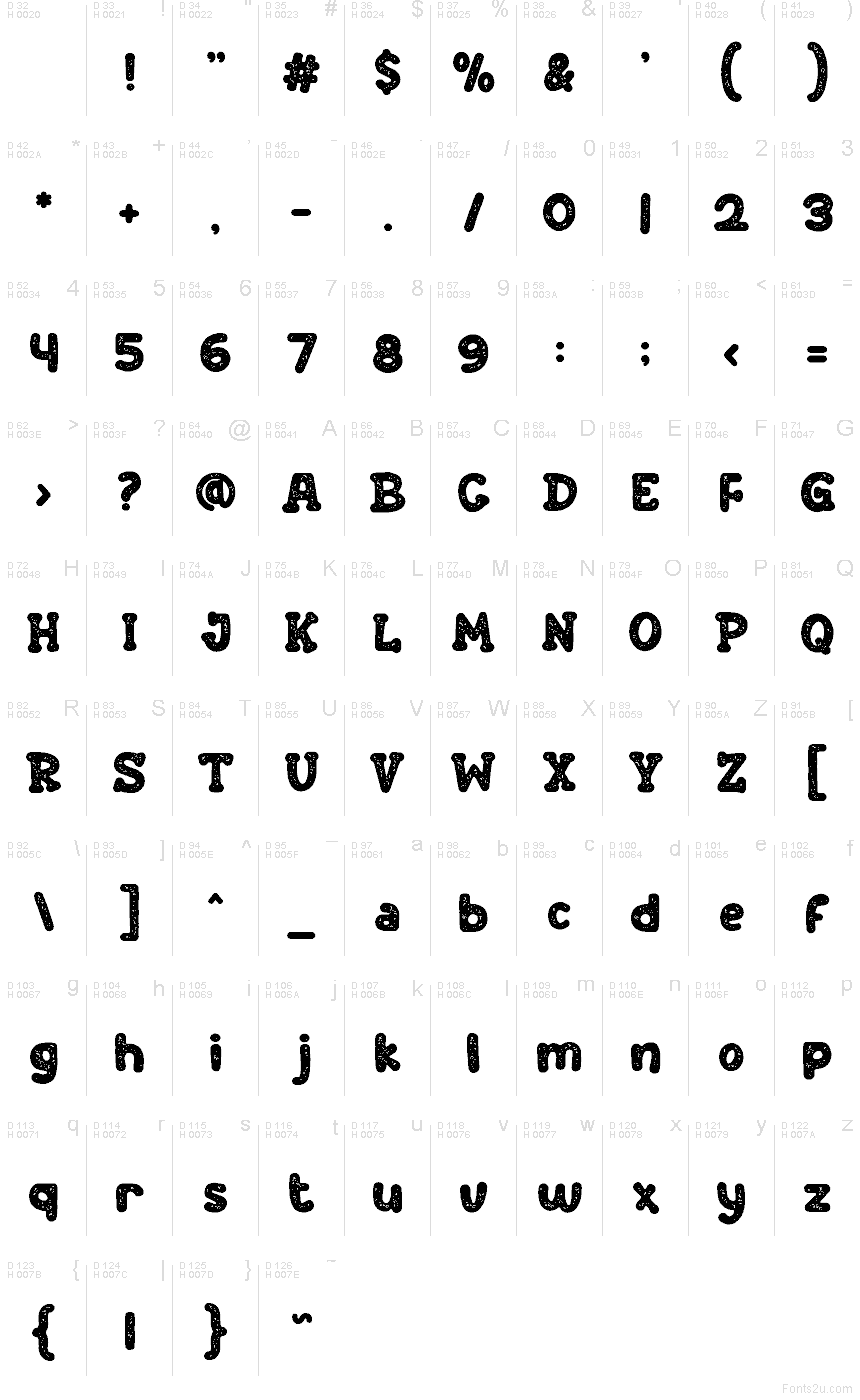
Crayon Craft Four od Putracetol Studio to bezpłatny, erodowany krój pisma typu display, stylizowany na rysunkowy. Charakteryzuje się miękkimi, zaokrąglonymi literami oraz woskową teksturą pełną przetartych drobinek. Ten efekt przypominający kredę i świecówkę przenika cały projekt, nadając czcionce rzemieślniczy, szkolny klimat, zamiast typowego, generycznego efektu postarzenia.
Świetnie sprawdzi się na okładkach książek dla dzieci, plakatach szkolnych, opakowaniach kreatywnych, zabawnych miniaturach na YouTube czy zaproszeniach na przyjęcia, gdzie jego pękata sylwetka przyciąga wzrok znacznie mocniej niż zwykły nagłówek. Chropowata powierzchnia sprawia, że idealnie pasuje też do kart pracy, zestawów naklejek i projektów DIY, dodając im autentycznego, ręcznie rysowanego charakteru.